Gợi ý font cho mỹ phẩm thiên nhiên, organic skincare và thương hiệu handmade
Gợi ý font mỹ phẩm thiên nhiên cho organic skincare, mỹ phẩm handmade, bao bì xanh, nhãn kraft và thương hiệu chăm sóc da tự nhiên.
Mỹ phẩm thiên nhiên, organic skincare và sản phẩm handmade cần một hệ chữ khác với mỹ phẩm công nghiệp hoặc beauty brand quá bóng bẩy. Font phải gợi cảm giác sạch, dịu, thật và có nguồn gốc tự nhiên, nhưng vẫn đủ chuyên nghiệp để khách tin vào chất lượng sản phẩm.
Một font mỹ phẩm thiên nhiên tốt cần đọc rõ trên nhãn chai nhỏ, hộp giấy, tem kraft, sticker cảm ơn và bài đăng social. Các cụm như “chiết xuất rau má”, “dầu dưỡng hữu cơ”, “xà phòng handmade”, “không paraben”, “dành cho da nhạy cảm” phải hiển thị rõ, không bị rối dấu tiếng Việt.
Bài viết này gợi ý 15 font TH Việt hóa phù hợp với organic skincare, mỹ phẩm handmade, bao bì xanh và brand organic. Mỗi font có ảnh preview và link tải để bạn chọn nhanh theo phong cách thương hiệu.
Font cho mỹ phẩm thiên nhiên cần tạo cảm giác gì?
Trước hết là cảm giác tự nhiên. Font không nên quá sắc lạnh hoặc quá công nghệ, vì nhóm sản phẩm organic thường bán sự dịu nhẹ, nguyên liệu thật và trải nghiệm chăm sóc lành tính. Serif mềm, script nhẹ hoặc sans-serif thanh lịch thường hợp hơn các font display quá mạnh.
Thứ hai là cảm giác đáng tin. Dù handmade, sản phẩm vẫn liên quan đến da và sức khỏe. Vì vậy, font cho thành phần, hướng dẫn dùng, dung tích, ngày sản xuất và hạn dùng phải rõ. Một bao bì đẹp nhưng khó đọc thành phần sẽ làm khách do dự.
Thứ ba là cảm giác thủ công vừa đủ. Handmade không có nghĩa là thiết kế phải thô. Bạn có thể dùng một font viết tay cho lời nhắn hoặc chữ ký, nhưng phần chính của nhãn vẫn nên có cấu trúc gọn và dễ đọc.
Tiêu chí chọn font organic skincare và bao bì xanh
Đọc tốt trên nhãn nhỏ
Nhãn serum, toner, son dưỡng, tinh dầu hoặc xà phòng thường có diện tích hạn chế. Hãy test font với tên sản phẩm, dung tích, thành phần và hướng dẫn dùng ở kích thước in thật trước khi chốt.
Hợp chất liệu kraft, giấy tái chế và nền xanh
Bao bì organic thường dùng giấy kraft, giấy mỹ thuật, nhãn trắng, màu xanh olive, be, nâu hoặc kem. Font cần đủ tương phản trên các nền này. Nét quá mảnh có thể đẹp trên màn hình nhưng yếu khi in trên giấy hút mực.
Giữ được tinh thần thương hiệu trên nhiều điểm chạm
Font không chỉ xuất hiện trên bao bì. Nó còn nằm trên website, landing page, bài social, catalogue, voucher, tem dán và hộp vận chuyển. Hãy chọn font có thể tạo hệ thống, không chỉ đẹp ở một poster.
Gợi ý font TH Việt hóa cho mỹ phẩm thiên nhiên, organic skincare và handmade
Danh sách dưới đây ưu tiên các font TH phù hợp với nhãn mỹ phẩm, bao bì xanh, sản phẩm handmade và hình ảnh skincare tự nhiên.
1. TH Retalin Regular
Phù hợp cho: spa thiên nhiên, skincare organic, nhãn serum, bao bì tối giản.
TH Retalin Regular có tinh thần làm đẹp nhẹ, sạch và tinh tế. Font phù hợp với mỹ phẩm thiên nhiên cần cảm giác dịu, không quá công nghiệp. Bạn có thể dùng Retalin cho tên thương hiệu, tên dòng sản phẩm, label serum hoặc hộp giấy tông trắng, xanh nhạt, be tự nhiên.
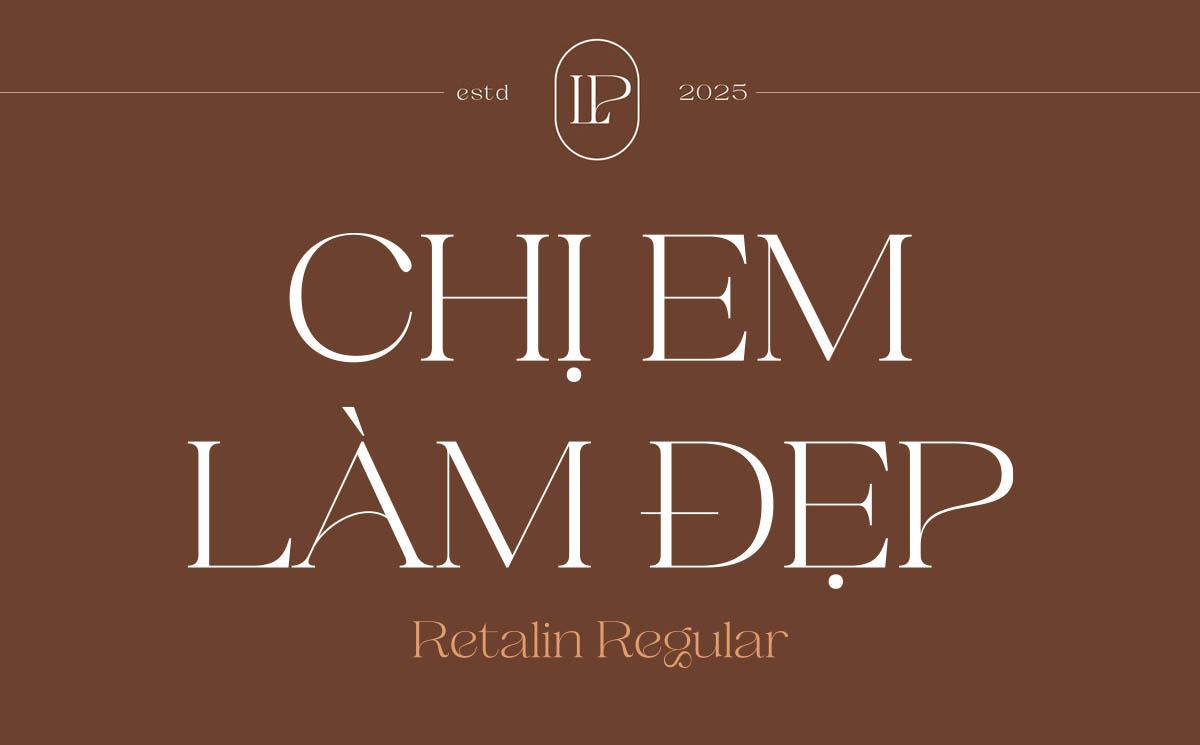
2. TH Meillona
Phù hợp cho: thương hiệu handmade, nhãn nến thơm, xà phòng thủ công, dòng sản phẩm mềm mại.
TH Meillona có nét uốn lượn trang trí, phù hợp với các sản phẩm handmade cần cảm giác cá nhân và thủ công. Font này đẹp khi dùng ở tên collection, dòng mô tả cảm xúc hoặc logo phụ. Không nên dùng Meillona cho thành phần, hạn dùng và hướng dẫn sử dụng vì nét trang trí sẽ làm chữ nhỏ khó đọc.
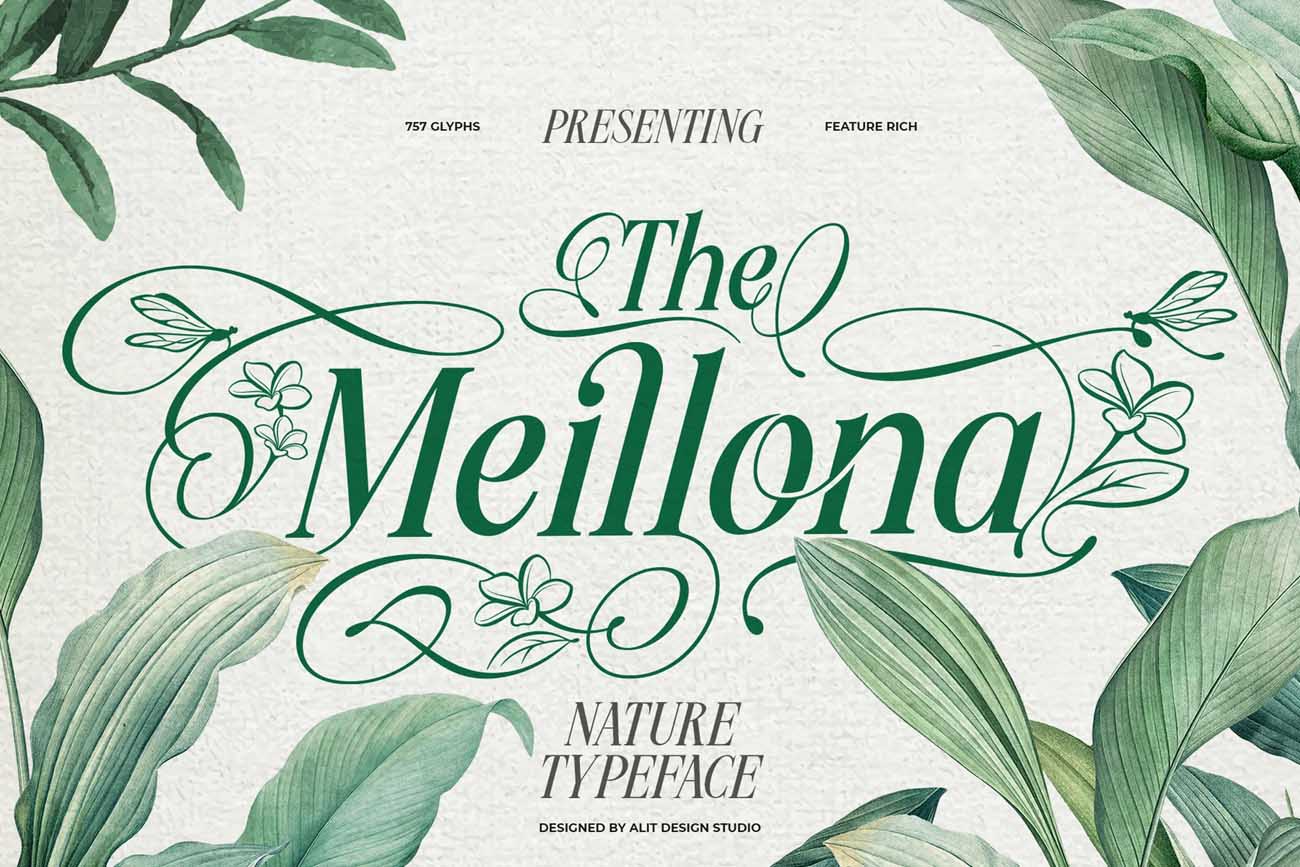
3. TH Luxury 6
Phù hợp cho: organic skincare cao cấp, thẩm mỹ xanh, poster chăm sóc da premium.
TH Luxury 6 mang vẻ hiện đại và sang, hợp với mỹ phẩm thiên nhiên ở phân khúc cao cấp. Font phù hợp cho tên sản phẩm, headline landing page, poster ra mắt serum hoặc bộ chăm sóc da organic. Khi phối, hãy dùng font phụ tối giản cho thành phần và thông tin kỹ thuật trên bao bì.
4. TH Billmake Regular
Phù hợp cho: bao bì mỹ phẩm cao cấp, nước hoa handmade, body oil, gift set.
TH Billmake Regular là serif sang trọng, hợp với những dòng mỹ phẩm thiên nhiên cần nâng cảm nhận giá trị. Font có thể dùng cho tên sản phẩm, nhãn hộp quà, bìa catalogue hoặc poster sản phẩm premium. Với bao bì xanh, Billmake tạo sự tương phản đẹp giữa chất organic và cảm giác boutique.
5. TH Mackenzin
Phù hợp cho: nhãn mỹ phẩm cổ điển, xà phòng thiên nhiên, trà thảo mộc, nến thơm.
TH Mackenzin có phong cách cổ điển, phù hợp với thương hiệu kể câu chuyện về nguyên liệu, vùng trồng, quy trình thủ công hoặc công thức truyền thống. Font này hợp với hộp xà phòng, nhãn lọ tinh dầu, trà thảo mộc và các sản phẩm có nền kraft hoặc giấy tái chế.
Font mỹ phẩm thiên nhiên nên tạo cảm giác sạch, dịu, có nguồn gốc tự nhiên và đủ đáng tin. Đừng chỉ chọn font vì đẹp trên mockup; hãy test trên nhãn thật, giấy thật và nội dung thật.
Nếu cần font cho organic skincare, mỹ phẩm handmade và bao bì xanh, bạn có thể bắt đầu với TH Retalin Regular, TH Luxury 6, TH Megan, TH Erva Esra, TH Selaris, TH Mackenzin, TH Buljirya hoặc TH Viettay 7. Phối đúng vai trò sẽ giúp thương hiệu vừa tự nhiên vừa chuyên nghiệp hơn.